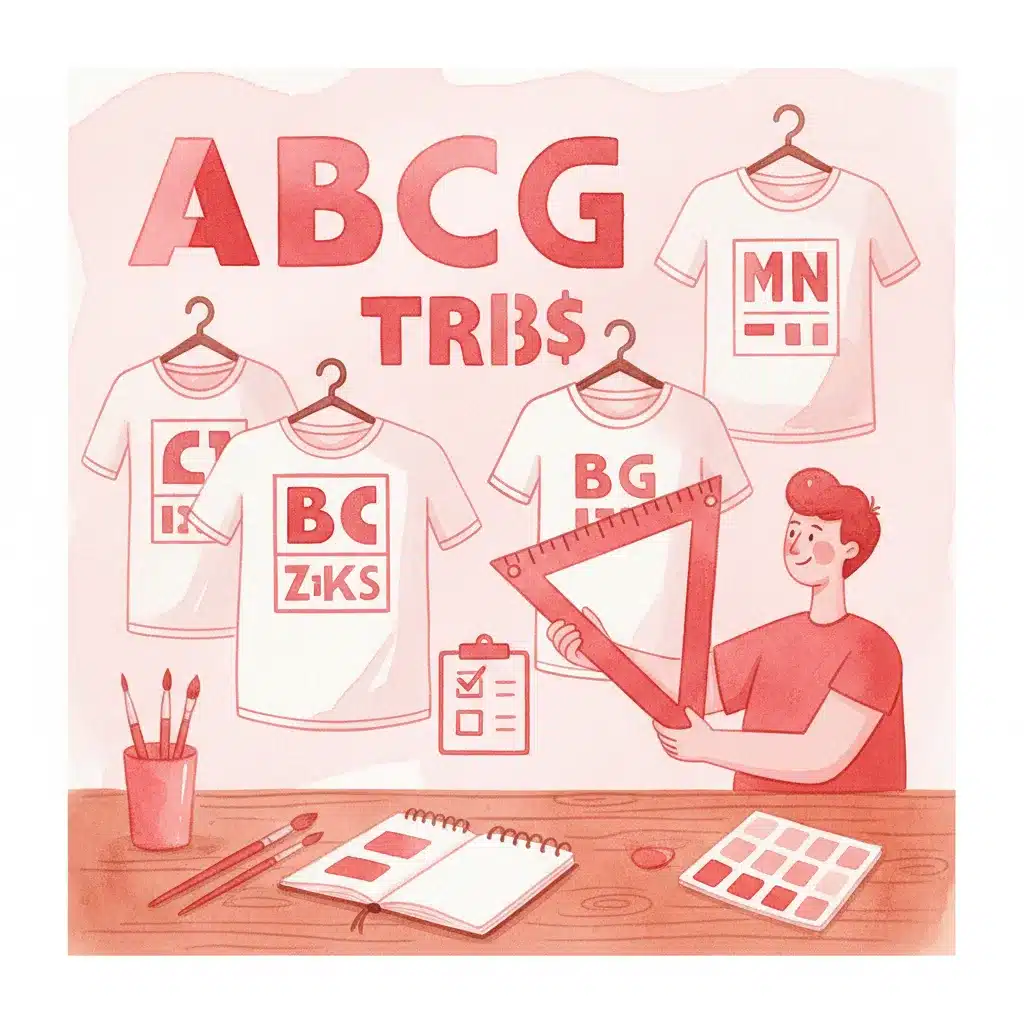
פונטים לחולצות: מה הכי נכון ומתאים
פונטים לחולצות הם אחד האלמנטים הקריטיים ביותר בעיצוב ביגוד ממותג – הם קובעים אם המסר יועבר בבהירות, אם המוצר ייראה מקצועי, ואם הקהל יתחבר אליו רגשית. בין אם מדובר בחולצת טי שירט לאירוע עסקי, מדים למוסד חינוכי, או חולצות קמפיין שיווקי – בחירת הגופן המתאים היא ההחלטה הטיפוגרפית שתשפיע הכי הרבה על התוצאה הסופית. מדריך זה מסביר שלב אחר שלב כיצד לבחור נכון.
- פונטים ללא סריף (Sans-serif) הם הבחירה הקלאסית לחולצות – קריאים, נקיים ומתאימים לרוב הסגנונות.
- גודל הטקסט, משקל הגופן וצבע ההדפסה משפיעים ישירות על הקריאות לאחר ייצור.
- יש להתאים את הפונט לאופי הקהל – פורמלי, מותגי, משחקי או ייצוגי.
- שגיאה נפוצה: שימוש בפונטים דקים מדי שנעלמים בהדפסה על בד.
פונטים לחולצות: מה הכי נכון ומתאים – מה הופך פונט לנכון לחולצות? עקרונות הבסיס
פונטים לחולצות הם גופנים שעוצבו או נבחרו כך שיתאימו להדפסה על בד – תוך שמירה על קריאות, עמידות ויזואלית ואיזון בין הטקסט לשטח הפנוי. הבחירה הנכונה תלויה בשלושה פרמטרים עיקריים: סוג הגופן (קטגוריה טיפוגרפית), משקל האות (עובי הקו), וסגנון העיצוב הכולל של החולצה.
לפי עקרונות הטיפוגרפיה המקצועית, פונטים ללא עיטורי סריף הם הבחירה הקלאסית לחולצות – הם קריאים, נקיים ומתאימים לכל סגנון. זאת מכיוון שעיטורי הסריף הקטנים עלולים להיעלם בהדפסת בד, במיוחד בגדלים קטנים או כשמשתמשים בטכניקות כמו רקמה. עם זאת, ישנם מקרים שבהם פונט סריף דווקא יעשה עבודה מצוינת – בעיקר בעיצובים קלאסיים, יוקרתיים או וינטג׳.
ארבעת קטגוריות הפונטים לחולצות
- Sans-serif (ללא סריף): הבחירה הנפוצה ביותר. קווים נקיים, קריאות גבוהה, מתאים לחולצות ממותגות, אחידות צוות ועיצובים מינימליסטיים. דוגמה לפונט עברי מתאים: פונט אספרסו – פונט sans-serif עם תמיכה דו-לשונית ומשקלים מרובים.
- Serif (עם סריף): מתאים לחולצות עם אופי קלאסי, פורמלי או אקדמי. עובד היטב בגדלים גדולים ובהדפסת מסך.
- Script / קליגרפי: פונטים בסגנון כתב יד. מתאימים לאירועים, חולצות כלה ורווקות, או עיצובים רומנטיים. יש לוודא שגודל האות מספיק גדול לקריאה.
- Display / כותרות: פונטים דרמטיים ובולטים המיועדים לכותרת אחת גדולה. עובדים מצוין כשהטקסט קצר ומרכזי בעיצוב.
כשמעצבים חולצות לאירועים ממותגים, כדאי לשקול פונטים קליגרפיים עם אופי – למשל, פונט אליאנה הוא פונט סקריפט קליגרפי דו-לשוני המתאים לאירועים ולכותרות. לפרטים נוספים על בחירת פונטים לפרויקטים שונים, ראו פונטים לעיצוב לוגו – המדריך המלא.
טעויות נפוצות בבחירת פונטים לחולצות – ואיך להימנע מהן
הניסיון בתחום עיצוב חולצות מלמד שרוב הבעיות בתוצר הסופי נובעות לא מהעיצוב הגרפי, אלא מבחירת פונטים לחולצות שלא נבחנו לפי מגבלות ייצור. אלה הטעויות הנפוצות ביותר:
5 טעויות שכדאי לדעת עליהן
- שימוש במשקל גופן דק מדי (Light / Thin): בהדפסת מסך ובגיהוץ, קווים דקים נשחקים ומיטשטשים. תמיד בחרו לפחות Regular, ועדיף Bold לטקסטים קצרים.
- טקסט קטן מדי: כיתוב מתחת ל-14pt בהדפסת מסך, או מתחת ל-18pt ברקמה – מסתכן בחוסר קריאות לחלוטין.
- פונט קליגרפי בגודל קטן: פונטים בסגנון כתב יד עם אותיות מחוברות נראים מרהיבים על המסך, אבל בגדלים קטנים על בד – הם עלולים להפוך לבלגן בלתי קריא.
- שילוב יותר מדי גופנים: שני פונטים שונים בעיצוב אחד הם המקסימום. שלושה פונטים ויותר יוצרים רעש ויזואלי ופוגעים במראה המקצועי.
איך בוחרים פונטים לחולצות לפי סוג הפרויקט?
לפי מומחים בתחום הטיפוגרפיה וחקר צרכנות, קיים קשר ישיר בין אופי הפרויקט לבין סוג הגופן שיתאים לו. חולצות ממותגות לחברות טכנולוגיה, לדוגמה, ידרשו גופן שונה לחלוטין מחולצות לאירוע חתונה או לקמפיין חברתי. הנה מדריך התאמה מהיר:
| סוג פרויקט | קטגוריית פונט מומלצת | משקל מומלץ |
|---|---|---|
| חולצות לחברה / מדים | Sans-serif נקי | Regular / Bold |
| חולצות לאירועים / חתונות | סקריפט / קליגרפי | Regular (גדול) |
| חולצות לקמפיין שיווקי | Display / כותרות | Bold / Extra Bold |
| חולצות למוסדות חינוך | Sans-serif / Serif | Regular / Bold |
| חולצות וינטג׳ / רטרו | Serif / מעוטר | Regular / Bold |
לעיצובים עם אופי קלאסי ומרשים, כדאי לשקול פונטים עם נוכחות חזקה – למשל, פונט מנדולינה, שמשלב אלגנטיות מובנית עם תנועה מודרנית ומתאים לכותרות בולטות. לעיצובים בסגנון תנ"כי-קלאסי, פונט שמיים – פונט סריף שעוצב על בסיס קליגרפיה קלאסית – יכול להעניק עומק ויוקרה לחולצה.
טיפים פרקטיים לבחירת פונטים לחולצות – צ׳ק-ליסט מלא
לפני שמגישים קובץ לייצור, עברו על הצ׳ק-ליסט הבא. כל סעיף שלא עמדתם בו – עשוי לגרום לתוצאה מאכזבת:
- ✓ הגופן שנבחר הוא לפחות Regular – לא Light ולא Thin.
- ✓ גודל הטקסט מינימלי 14pt בהדפסת מסך, 18pt ברקמה.
- ✓ נבדקנו שהפונט קריא בתצוגה מוקטנת (Mockup על חולצה).
- ✓ השתמשנו בלא יותר משני גופנים בעיצוב אחד.
- ✓ בדקנו את רישיון הפונט לשימוש מסחרי (אם החולצות נמכרות).
- ✓ הפונט הומר ל-Outlines (עקומות) לפני שליחה לייצור – כדי למנוע בעיות עם קובץ.
- ✓ הצבע המתוכנן מתאים לטכניקת ההדפסה (מסך, סובלימציה, רקמה).
לפי עקרונות ה-Google Fonts ומומחי טיפוגרפיה, שילוב של פונט ראשי בולד עם פונט משני קל יותר יוצר היררכיה ויזואלית ברורה – ומסייע לעין לנווט בין המסר הראשי לפרטים המשניים בחולצה.
תהליך בחירת פונטים לחולצות ב-4 שלבים
הצעד הבא: בדקו Mockup, עברו על הצ׳ק-ליסט, ואשרו את רישיון הפונט לפני שליחה לייצור. עיצוב מוצלח מתחיל בבחירה מושכלת.
רעיונות ליישום מיידי:
1. חולצת ממותגת לחברה – נסו פונט Sans-serif Bold עם שם החברה בלבד, ללא עיטורים מיותרים.
2. חולצה לאירוע חתונה – שלבו פונט קליגרפי לשמות עם פונט נקי לתאריך ומיקום.
3. חולצת קמפיין – בחרו פונט Display גדול עם מסר אחד חזק – פחות טקסט, יותר השפעה.